카드뉴스 만들 때 가독성과 감성을 동시에 잡는 폰트 조합이 중요합니다.
너무 감성적이면 읽기 힘들고, 너무 딱딱하면 매력 없죠!
📌 1. 넥슨 Lv1 고딕체 + 배민체
- 넥슨 Lv1 고딕체: 본문용으로 깔끔한 인상
- 배민체: 헤드라인에 감성 더하기
📌 2. 서울한강체 + 야놀자 야체
- 서울한강체: 균형잡힌 가독성
- 야놀자 야체: 포인트 강조에 적합
📌 3. 티몬체 + 메로나체
- 티몬체: 깔끔하고 힘있는 제목 폰트
- 메로나체: 여름 테마에 어울리는 포인트 글
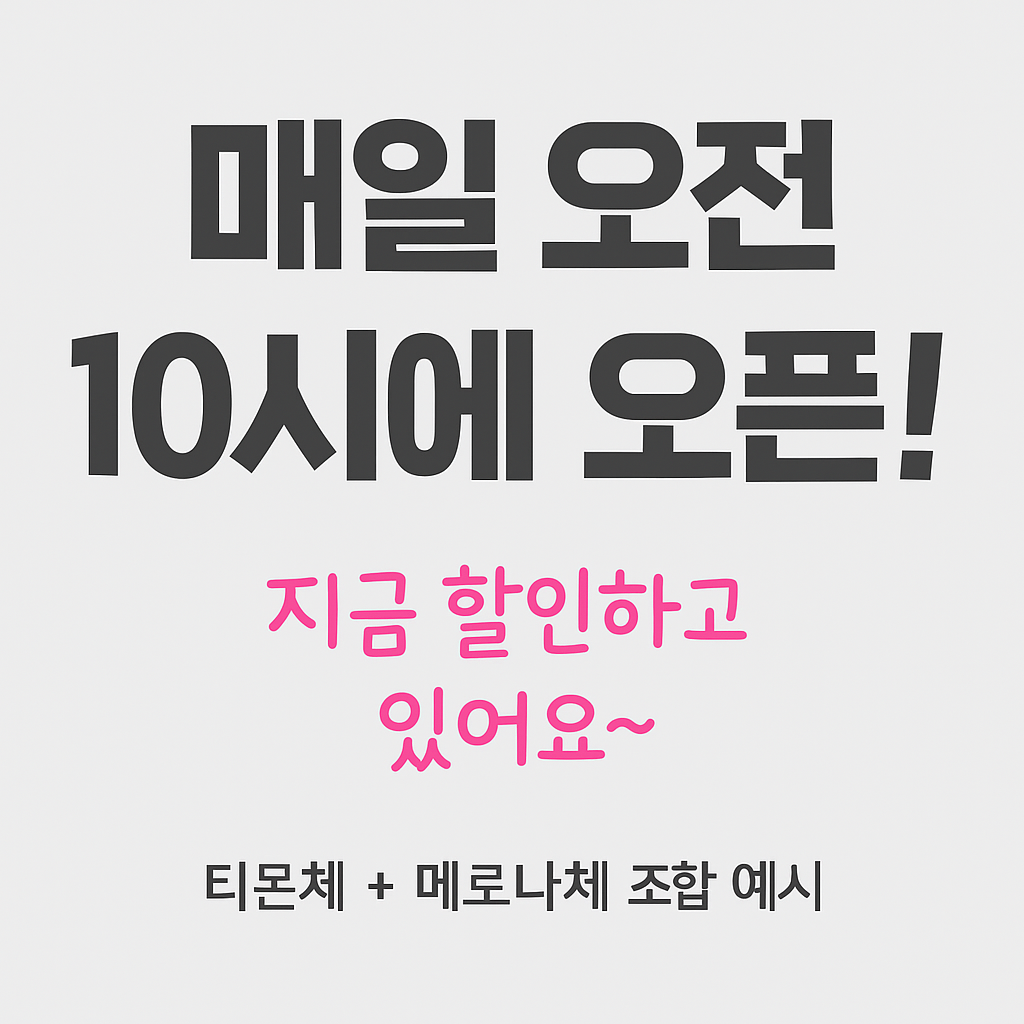
📌 4. IBM Plex Sans KR + 배민주아체
- IBM Plex Sans KR: 프로페셔널한 카드뉴스용 본문
- 배민주아체: 감성 터지는 헤드라인
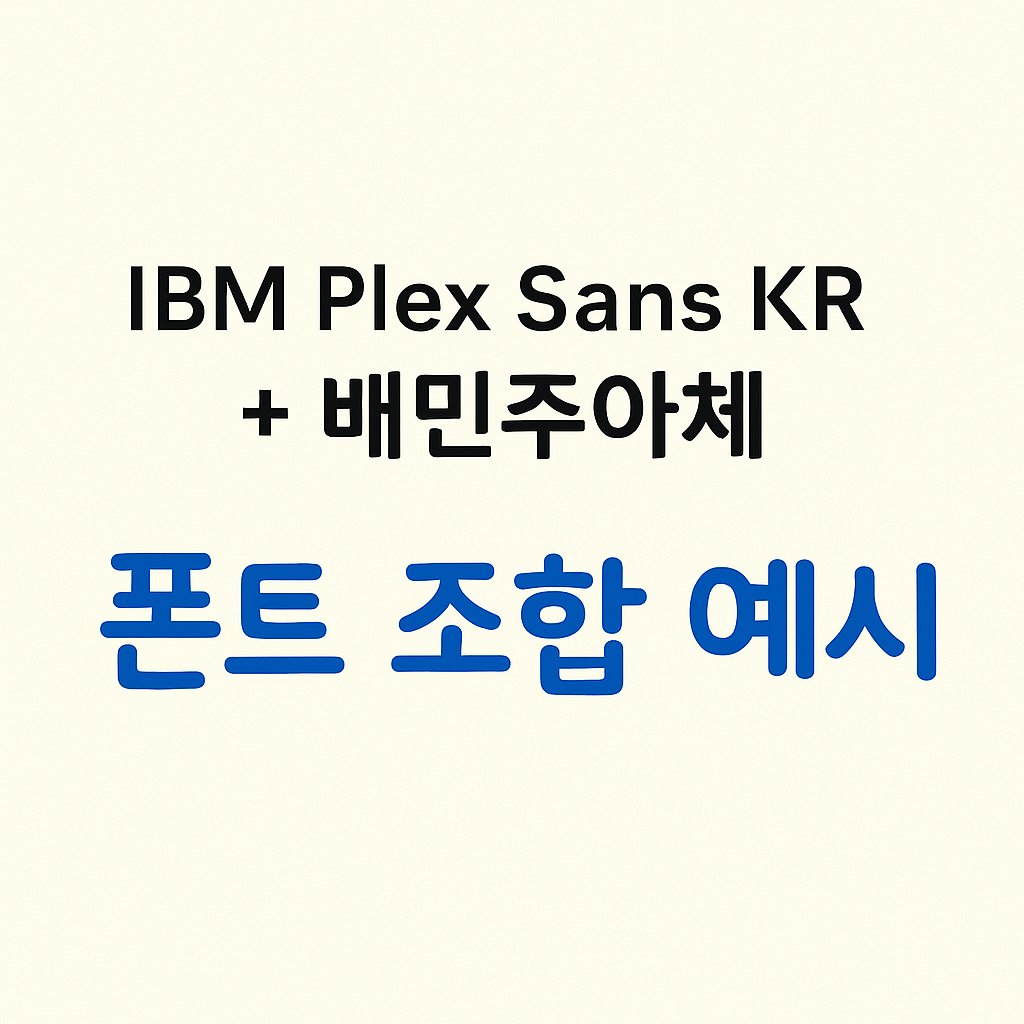
📌 5. 카페24 써라운드체 + 빙그레체
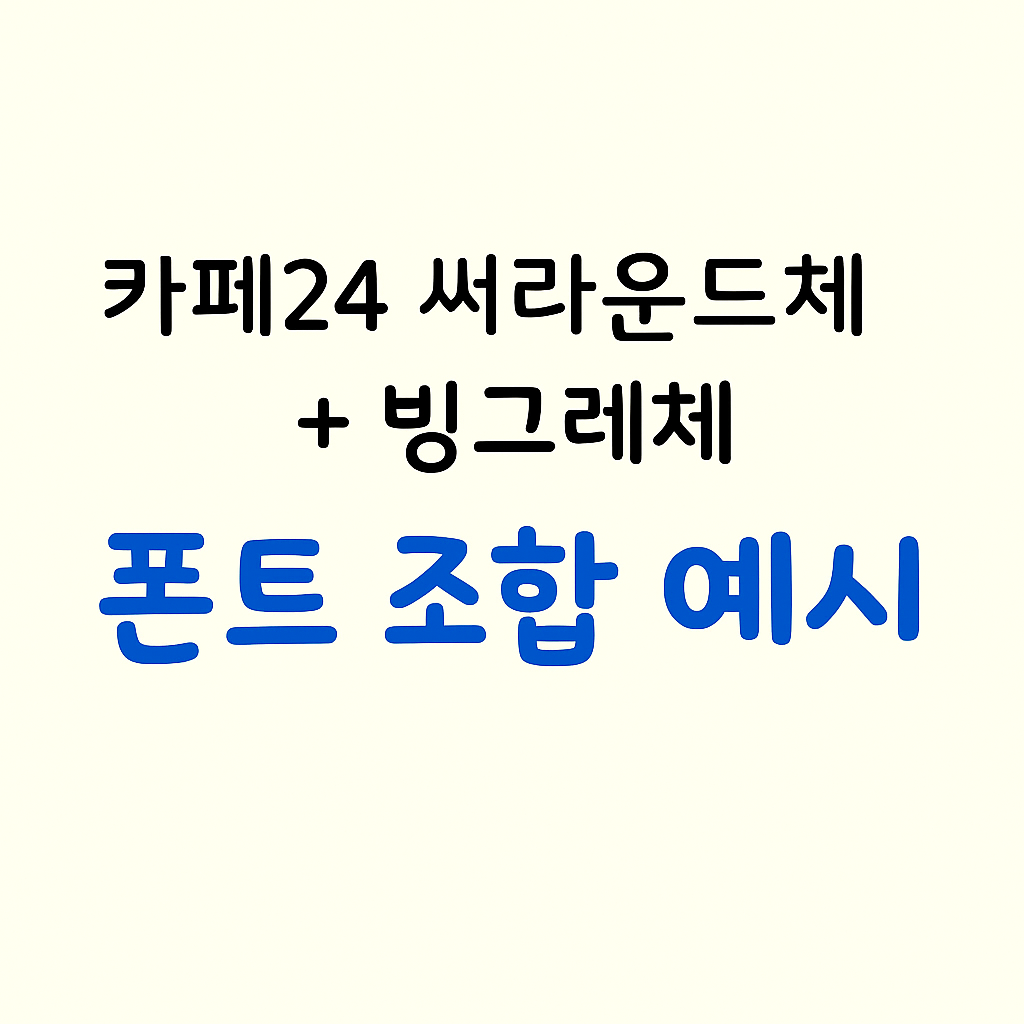
- 카페24 써라운드체: 제목 강조용 폰트
- 빙그레체: 부드러운 손글씨 느낌
💡 꿀팁!
✔ 제목용 / 본문용 / 포인트용으로 폰트 역할 분리가 중요합니다.